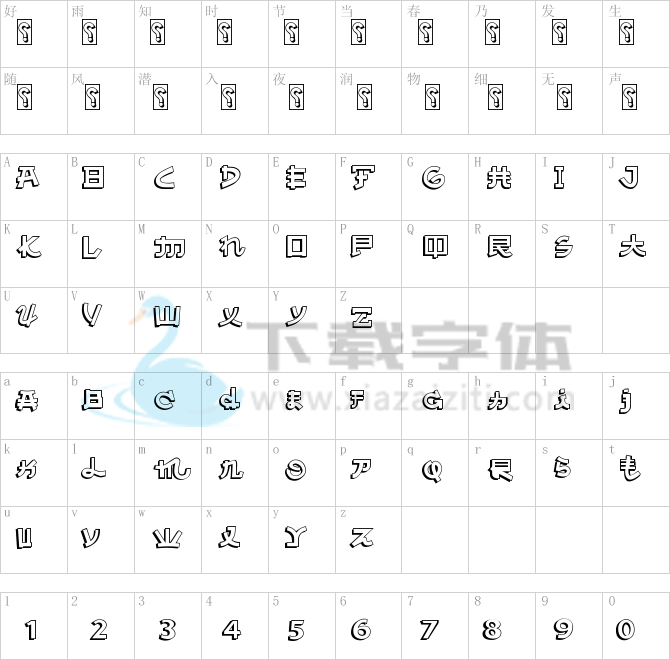
Almost Japanese Comic.ttf字体下载,这款字体结构工整、笔画清晰,兼顾美观与易读性,适用于标题、正文、海报、包装、LOGO 等多种场景。字形优雅稳定,风格百搭耐看,适配日常排版与创意设计,让文字呈现更舒适、更具质感。Almost Japanese Comic.ttf字体下载一笔一画,皆是细节,以均衡的比例、流畅的线条打造舒适视觉体验,字形端正大气,风格简约现代。无论是商业设计、品牌宣传还是日常排版,都能轻松驾驭,让文字更有格调与力量。Almost Japanese Comic.ttf字体下载字体下载。
• 字体名称:Almost Japanese Comic